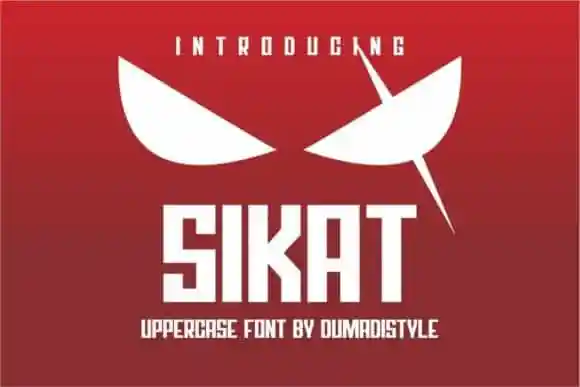
Sikat Display Font – Download Grátis
A Sikat Display Font é uma elegante serifless tipo moderna projetada para composições de tipos em suas criações. Suas linhas retas e formas simples criam um design limpo que se adapta perfeitamente a designs gráficos, como posters ou headlines, garantindo que suas mensagens ganhem uma primeira impressão memorável. Ideal para headlines, rótulos, identidades visuais e embalagens de produto, a Sikat Display é perfeita quando você deseja transmitir seu design de maneira moderna e atraente. Suas características neutras e limpas permitem que ela seja usada em uma variedade de contextos sem perder sua elegância, tornando-a uma fonte ótima para designers gráficos profissionais.